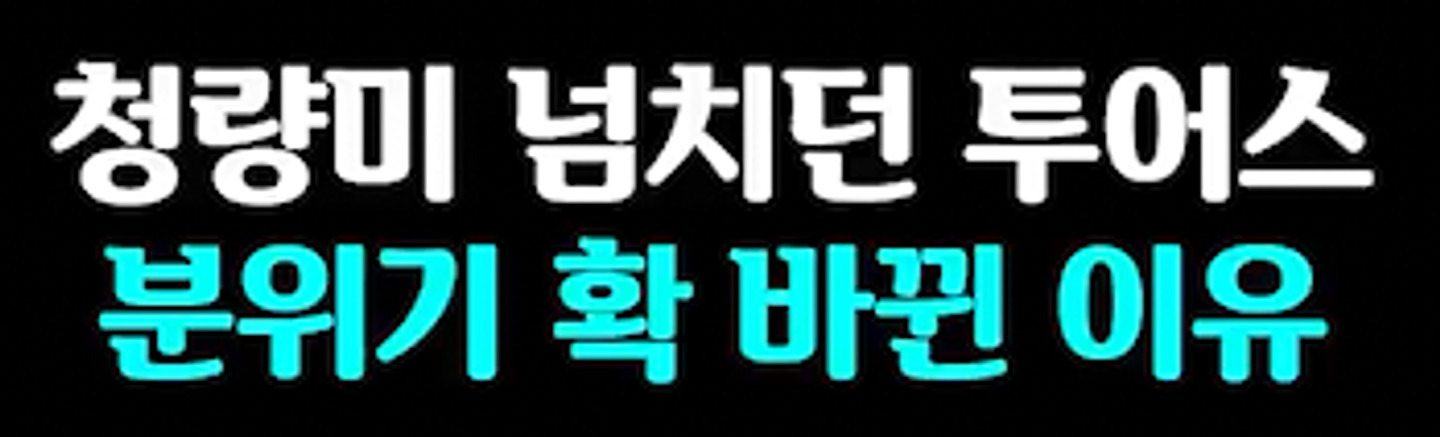
프리텐다드 폰트입니다! 글자 장평 조정했네요! Ai 올컷님이 제작하신 느좋폰트 사용하시면 이미 장평이 조정되어 있는 폰트라 따로 조정 안 하셔도 됩니다! https://blog.naver.com/aiollcut/224378366021?trackingCode=blog_bloghome_searchlist